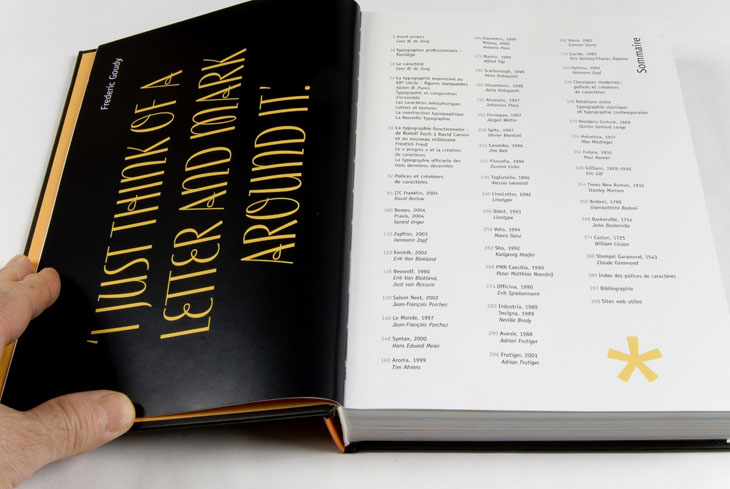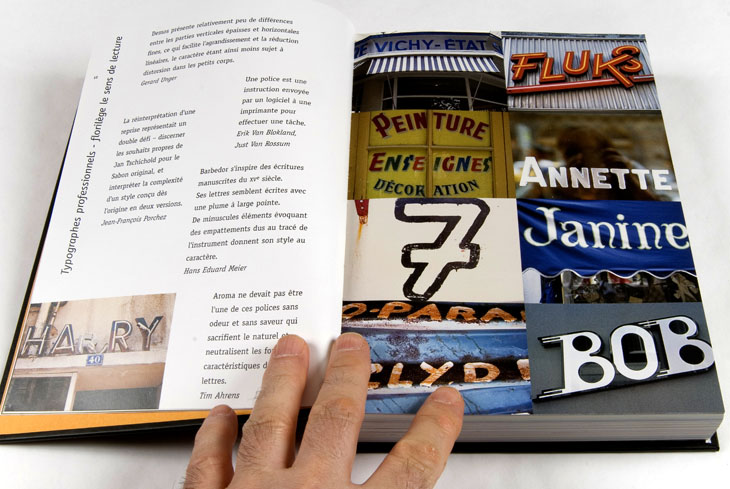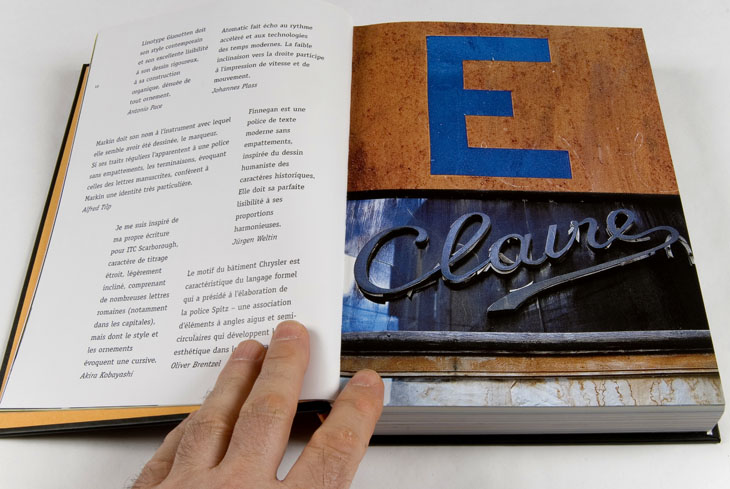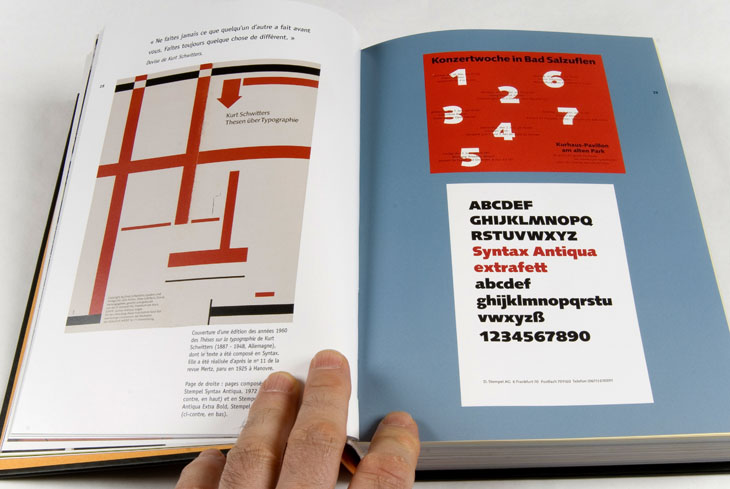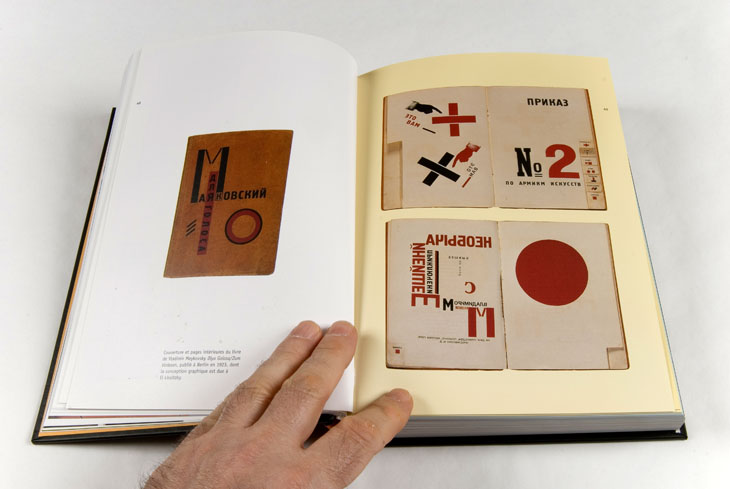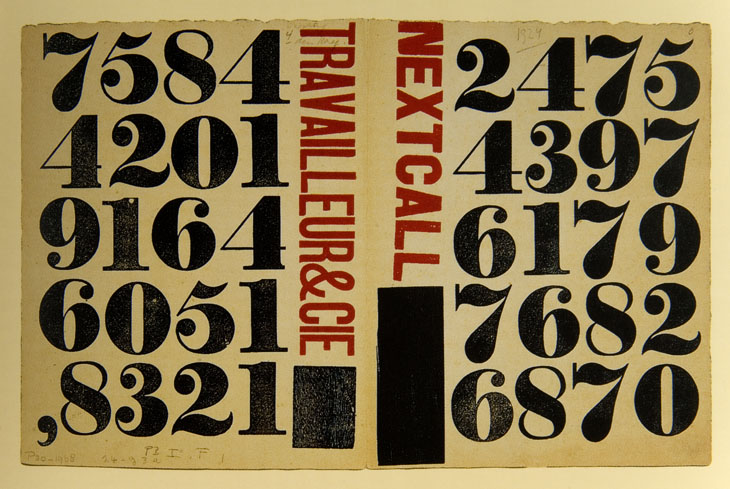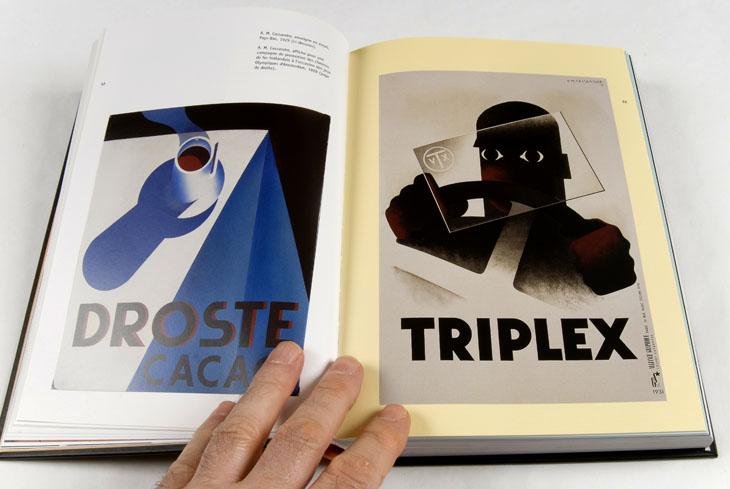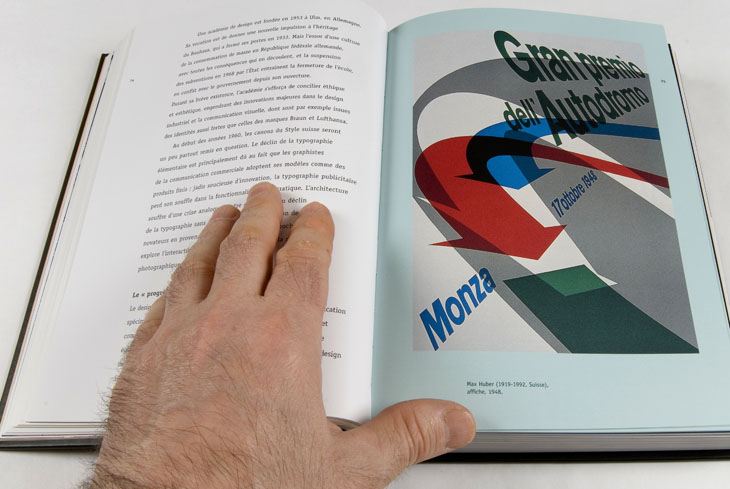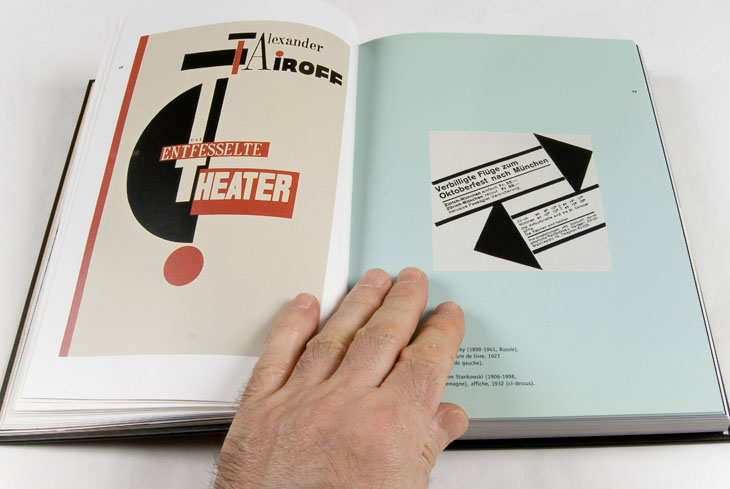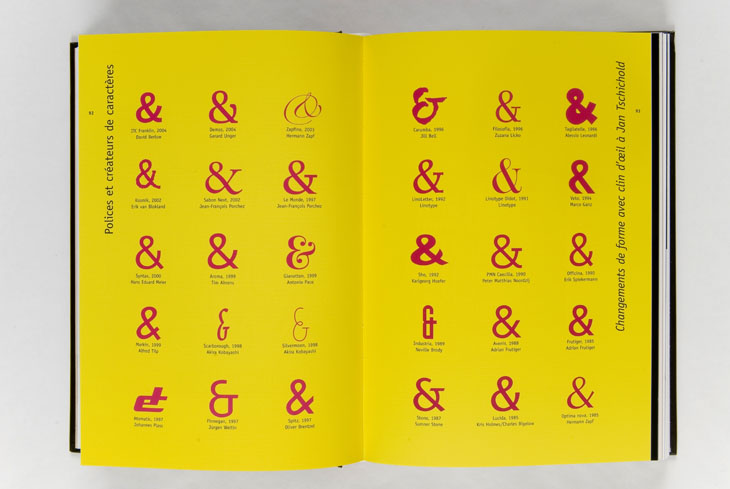
Créations Typographiques | La Typo passionne les Éditions Eyrolles
Voici enfin une étude que j’ai réalisé sur l’ouvrage édité par les éditions Eyrolles intitulé <Création Typographiques > de 1985 à nos jours. Je dois vous avouer que cette étude a été menée en plein accord avec l’éditeur qui m’a laissé toutefois l’entière liberté de parole pour encenser ou désavouer son travail.
Dans l’avertissement au lecteur, Eyrolles nous prévient qu’il s’adresse avant tout aux designers débutants, ce en quoi il a raison et tort à la fois. Raison, quand il s’agit d’évaluer le travail au regard de ses qualités académiques, tort lorsqu’il s’agit de l’estimer en tant qu’œuvre documentaire relatant la somme des exemples typographiques cités.
Tort tout d’abord. Ce n’est pas la première fois que nous voyons le fonds graphique ici présent. L’éditeur hollandais Cees W. De Jong avait déjà publié un ouvrage *Graphic Design in XXe century*. Je l’avais moi-même relaté dans les colonnes de D&T ici .
Je me souviens qu’une des principales critiques soulevées concernait l’absence de Herbert Lubalin dans cette édition. Absence qu’on ne pourra cette fois repprocher dans le présent ouvrage puisque son corpus concerne la période allant de 1985 à nos jours. Sauf à considérer l’introduction historienne du livre qui remonte au début du siècle et parcourt rapidement toute la période antérieure aux années 85.
Ma principale critique de Créations Typographiques ne porte pas au contenu visuel de l’ouvrage. Cees W. De Jong nous a habitué au travers de son extraordinaire fonds iconographique à porter à notre regard les meilleurs travaux graphiques publiés dans le monde. Et s’il fallait en remercier l’auteur ne serait-ce que pour cette raison, ce serait déjà suffisant. Mais quid de l’aspect académique. Je m’adresse à des débutants designers, des étudiants donc, ou des professionnels fraîchement sortis des écoles. Je me dois donc vis à vis d’eux de procéder selon un schéma quasi scolaire, du moins pédagogique en:
introduisant
chapitrant
rubriquant
et en châpotant les articles.
Rien de tout cela. Non que le metteur en page ait conçu une architecture personnelle et originale, mais parce qu’il ya absence de tout ces outils de lecture qui permettent justement à des débutants de commencer un ouvrage à la page une et de le finir à la page 396. *Créations Typographiques de 1985 à nos jours* est un livre visible mais pas lisible. Je ne suis entré à aucun moment dans une lecture ordonnée de l’histoire, pas compris la raison de tel ou tel choix de créateur typographe. Prenons un exemple: récemment j’avais publié ici les statistiques de préférences typographiques constatées par un graphiste Tchèque. Pour le monde entier. Ces mêmes statistiques corroborent celles publiées régulièrement par Fontshop.de qui nous informe de leurs meilleures ventes, mois après mois. On aurait pu imaginer qu’une histoire de la typographie parte de constats, ceux de l’usage quotidienne. Ou bien par exemple que l’on prenne la liste de tous les fonts awardés dans le monde, on arriverait à un autre résultat, mais toujours aussi cohérent. Là rien. C’est un mélange incohérent des typos, qui jamais, ne sera, ne pourra être exhaustif sauf à prévoir une pagination de trois à quatre mille pages.
Parce que faire un livre sur la typographie, c’est évidemment, prendre le parti de montrer les alphabets et leur utilisation. Il n’y a pas secteur marketing plus mangueur de papier que celui de la typographie. Un alphabet est constitué de 26 lettres en capitales et bas de casses, plus les chiffres et ponctus. Si on veut se donner la peine on pourrait faire l’étude d’un alphabet lettre par lettre, signe par signe. Ainsi ci-dessous deux signes, esperluettes provenant d’un des plus beaux caractères d’imprimerie, le Palatino romain et italique de Hermann Zapf. C’était sans doute l’occasion pour l’éditeur quand il aborde l’article le Zapfino de montrer et pas seulement énumérer, le cheminement graphique d’Hermann Zapf qui en arrive à cette calligraphie hors normes, tellement racé et personnel à la fois. Mais c’est vrai, je le disais plus haut, la typographie est mangeuse de papier. A croire que internet et la publication électronique serait plus appropriée à ce type de publication que le papier traditionnel.
Va pour le papier. Je voudrais pas laisser le lecteur de cette note sur une mauvaise impression ;-), parce que le sujet est épineux. L’on a du mal à suivre une ligne éditoriale et l’on tombe rapidement dans la “monstration” sans discernement qualitatif. Juste parce que le sujet est spectacle tout autant qu’outil de communication. Mais attention. Vous qui feriez parti de ces débutants sans trop de référents catégoriels, ne vous désolez pas, même si vous vous perdez au beau milieu de cet ouvrage, faute de grille de lecture claire et pédagogique, il n’en demeure pas moins un must des exemples montrés, par la qualité des choix, et la diversité des styles. N’hésitez pas à nous laisser vos commentaires.